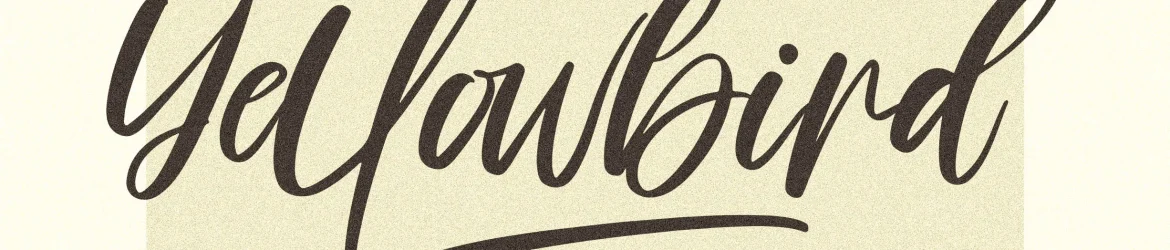
Esta é uma fonte escrita a mão perfeita para uma variedade de projetos criativos. Perfeita tanto para logotipos ou projetos de identidade, designs de móveis de casa e embalagens, etiquetas e rótulos, capas de livros, cartões de nome, convites e cartões festivos, até mesmo marcas para fotografias e bordados em eventos especiais. Ideal para adicionar um toque único e autêntico a seus projetos luxuosos. A Yellowbird Font é perfeita para qualquer projeto que necessite daquela pitada de escrita à mão especializada. Ela foi criada pelo designer perspectype, ideal para aqueles interessados em uma fonte com um sabor pessoal e autêntico.